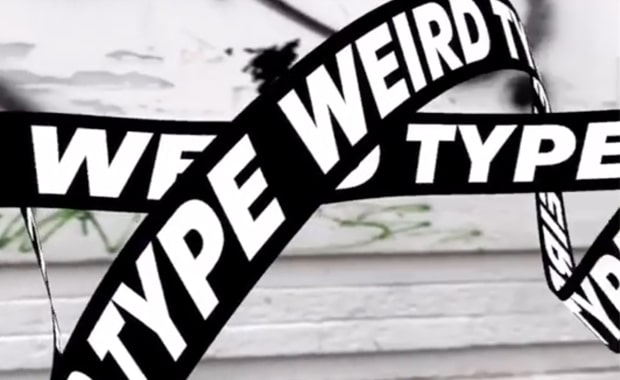
Typografie 2.0: Schriftdesign im freien Raum
Sie hat dieses hässliche Graffiti in der Stadtmitte an der Bahnhofsmauer schon immer gestört? Und Sie würden am liebsten selbst gerne drüber malen bzw. schreiben? Natürlich ist das in der Realität auch weiterhin verboten – doch dank AR-Technologie und der genialen iOS-App des New-Media-Künstlers Zachary Lieberman können Sie jetzt endlich eingreifen. Und das ohne Ärger mit den Gesetzeshütern zu bekommen!
Typografie trifft auf Augmented Reality
Die App »Weird Type« von Zach Lieberman ermöglicht es dank Augmented Reality (AR), mit dem iPhone kreativ Text in den freien Raum zu projizieren und dort quasi schweben zu lassen. Die Grenze zwischen Realität und künstlicher Welt verschwimmt, Schrift und Texturen aus der Umwelt gehen ineinander über. Die Aufnahmen bzw. geschriebenen Nachrichten lassen sich als Video speichern und mit anderen Menschen teilen.